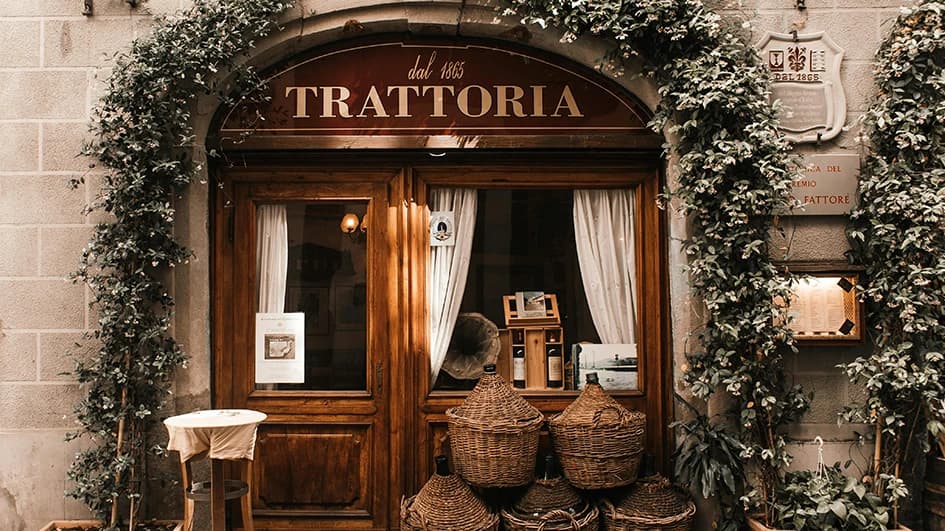
Quelle typographie choisir pour le logo de son restaurant ?
Quelle typographie utiliser pour son logo en fonction du type de restaurant ? Découvrez toutes les clés d'une graphiste professionnelle !
En bref : la typographie du logo de votre restaurant doit refléter votre cuisine : une serif classique comme la Garamond pour un établissement traditionnel, une sans serif épurée comme la Futura pour une table végétale ou vegan, une display audacieuse pour un concept innovant, des empattements épais façon Rockwell pour la viande et les burgers, et une Didot ou une Bodoni pour la gastronomie.
Bienvenue sur le blog de Citron Sorbet, votre spécialiste en création de logo et identité visuelle à Nantes et ses alentours. Aujourd’hui, nous allons explorer ensemble un aspect crucial de la création d’identité de marque : le choix de la typographie pour votre logo, spécifiquement adapté au type de votre restaurant. Que vous soyez un établissement traditionnel, végétal ou vegan, innovant, spécialisé en viande/burger, ou un restaurant gastronomique, le choix de la police d’écriture peut transformer la perception de votre marque.
L’importance de l’authenticité pour les restaurant traditionnels
Pour un restaurant de cuisine traditionnelle et de terroir, la typographie doit évoquer l’authenticité et la confiance. Utilisez pour votre logo des polices avec une touche d’élégance rétro, comme les typographies serif classiques. Par exemple, des polices telles que Garamond ou Times New Roman, avec leurs courbes subtiles et leur prestance intemporelle, peuvent parfaitement communiquer les valeurs d’authenticité et de simplicité de votre restaurant. Avec ce type de polices, vous ne pouvez pas vous tromper ! Elles racontent une histoire, celle de votre restaurant ancré dans les traditions, tout en promettant une expérience culinaire rassurante et de qualité.
La fraîcheur à l’honneur pour les restaurants végétaux et vegan
Les restaurants végétaux ou vegan peuvent tout à fait opter pour des polices d’écriture modernes et épurées, reflétant la fraîcheur et la légèreté de leurs plats. Des typographies sans serif, comme par exemple la Helvetica ou l’indémodable Futura, sont idéales pour communiquer une image de marque contemporaine et consciente des enjeux environnementaux. Leur simplicité visuelle s’aligne avec les valeurs de transparence et de bien-être associées à la cuisine végétale. Elles allient parfaitement la simplicité (des produits) et la modernité et sont tout indiquées pour votre type de restaurant.
Osez la différence pour les restaurants innovants
Les restaurants à la pointe de l’innovation culinaire devraient à mon sens opter pour des polices de caractère qui sortent de l’ordinaire. Des typographies display telles que la Big Shoulder ou futuristes comme la Geomanist, peuvent marquer les esprits et souligner votre côté avant-gardiste. L’objectif est de susciter la curiosité et d’inviter vos clients à découvrir l’expérience culinaire unique que vous leur proposez.
Robustesse et convivialité pour les restaurants de viande et les restaurants de burgers
Pour un restaurant spécialisé dans la viande ou les burgers, on préférera une typographie qui allie des valeurs de robustesse et de convivialité. Des polices à empattement épais, comme la Rockwell ou la Abril FatFace, sont parfaites pour transmettre cette sensation de générosité et de plaisir gourmand. Elles reflètent la nature copieuse de vos plats et créent une atmosphère accueillante et chaleureuse.
L’élégance au premier plan pour les restaurants gastronomiques
Pour un restaurant gastronomique, la sophistication et le goût de l’excellence doivent transparaître à travers chaque détail, y compris la typographie de votre logo. Des polices élégantes et raffinées, comme la Didot ou la Bodoni, avec leurs contrastes marqués et leurs courbes délicates, peuvent magnifiquement véhiculer l’exclusivité et l’excellence de votre établissement. Elles suggèrent une expérience culinaire hors du commun, où chaque plat est une œuvre d’art.
Exemples de typographies utilisées par les grandes enseignes de restauration
La typographie d’un logo joue un rôle clé dans l’identité visuelle d’un restaurant, reflétant sa personnalité, ses valeurs et sa niche culinaire. Voici quelques exemples de restaurants connus et les typographies de leurs logos, illustrant comment ces choix contribuent à leur image de marque :
- McDonald’s utilise une typographie simple mais très reconnaissable avec son « M » emblématique en arc jaune. La police utilisée est une variante de la « Mclawsuit », très amicale et accessible, ce qui en fait un choix parfait pour un restaurant de fast-food visant une large audience.
- Starbucks opte pour une police de caractères sur mesure nommée « Freight Sans Black ». Le résultat est à la fois sophistiqué et accueillant, et reflète ainsi l’ambiance cosy des cafés Starbucks et leur engagement envers la qualité et le confort.